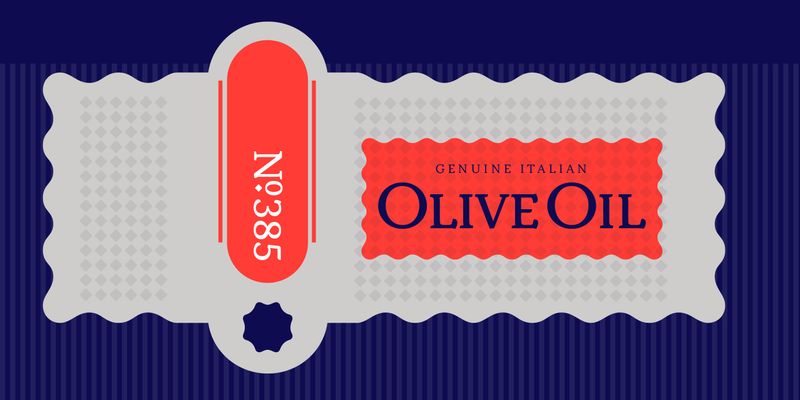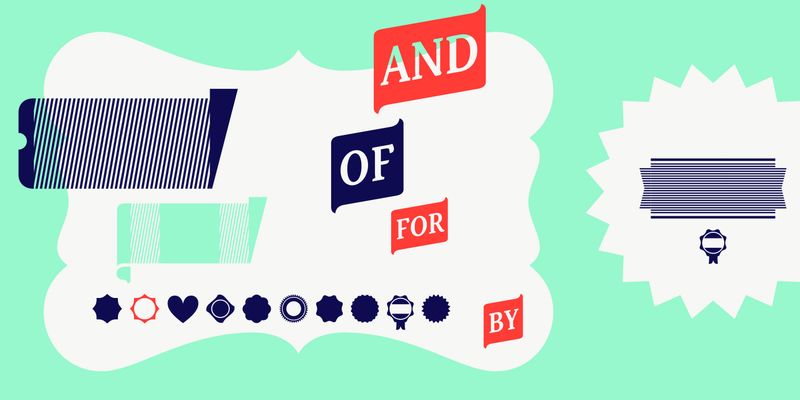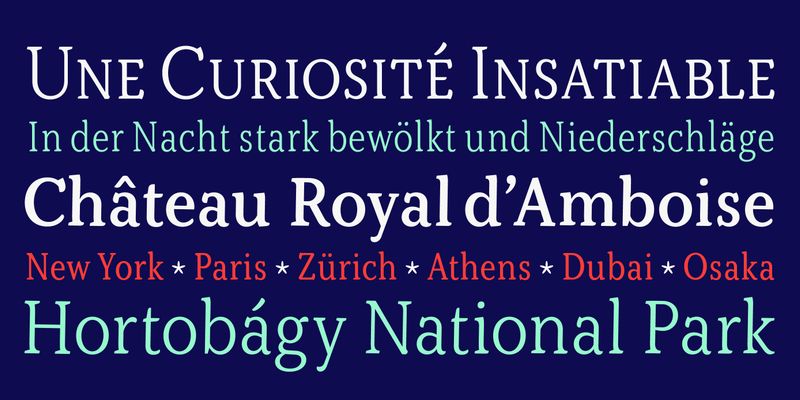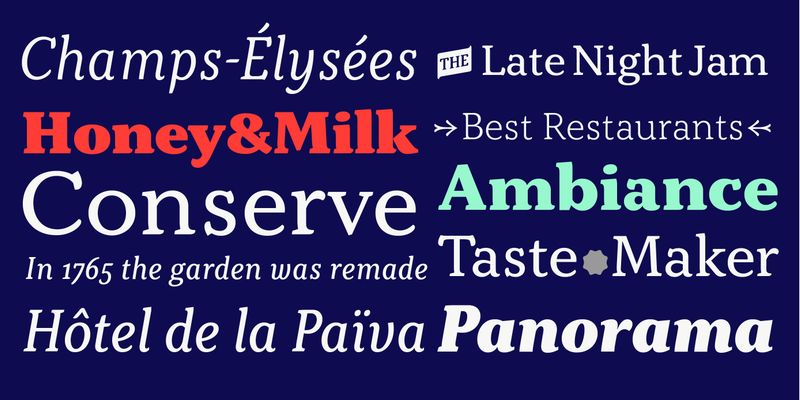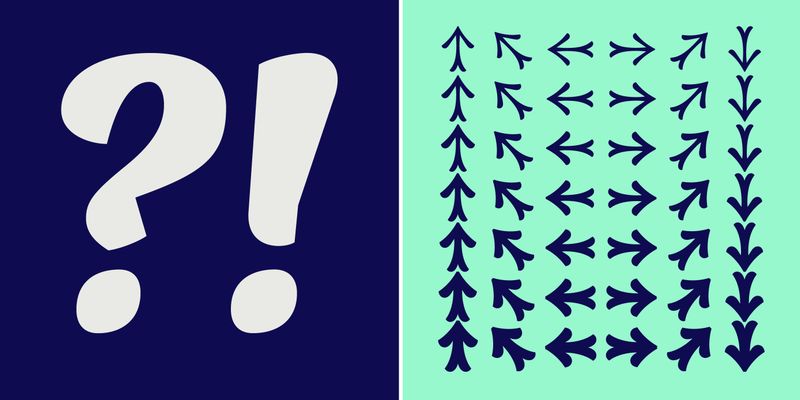
La familia Kopius es un tipo serif contemporáneo que presenta características sencillas con blancos internos redondos y abiertos que transmiten un look relajado. La solidez de los caracteres admite una amplia variedad de aplicaciones, incluido el uso editorial y cartelería.
La nueva construcción de glifos y las formas serif definidas de forma única transmiten una alusión a un trazo de pincel que otorga un aspecto contemporáneo rico en texturas, totalmente en sintonía con la funcionalidad. Las astas ascendentes y descendentes ligeramente curvadas implican flujo y dirección de lectura.
Kopius es una familia exuberante con un repertorio genuinamente multifacético. Este tipo alegre viene con una multitud de grosores para satisfacer cualquier apetito imaginativo por una paleta tipográfica colorida. Con las soluciones de embalaje en mente, la familia incluye juegos de material de encabezado de caja expandible y combinable para una gama ilimitada de materiales compuestos ajustados.
Además, las etiquetas pertinentes, las flechas de grosor ajustado y los logotipos de palabras completan la familia Kopius. OpenType proporciona funciones de diseño avanzadas que incluyen conjuntos de figuras, versalitas, fracciones y más.
Liberta de Herbert Thannhaeuser, una familia tipográfica Antiqua diseñada para la casa de tipografías de Alemania Oriental VEB Typoart entre mediados y finales de la década de 1950, ha despertado la fuerza inspiradora inicial de Kopius. Con su comportamiento afable pero serio, Kopius asume con confianza numerosas tareas.